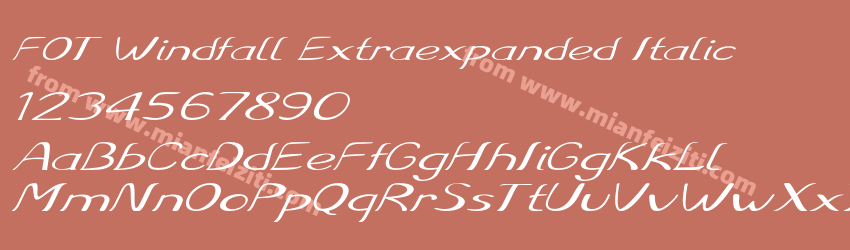
FOT Windfall Extraexpanded Italic
字体名称: FOT Windfall Extraexpanded Italic
Postscript名称: FOTWindfall-ExtraexpandedItalic
本款“FOT Windfall Extraexpanded Italic”是一款书写很新颖的字体,字体大方,适合各种设计作品使用!欢迎下载!